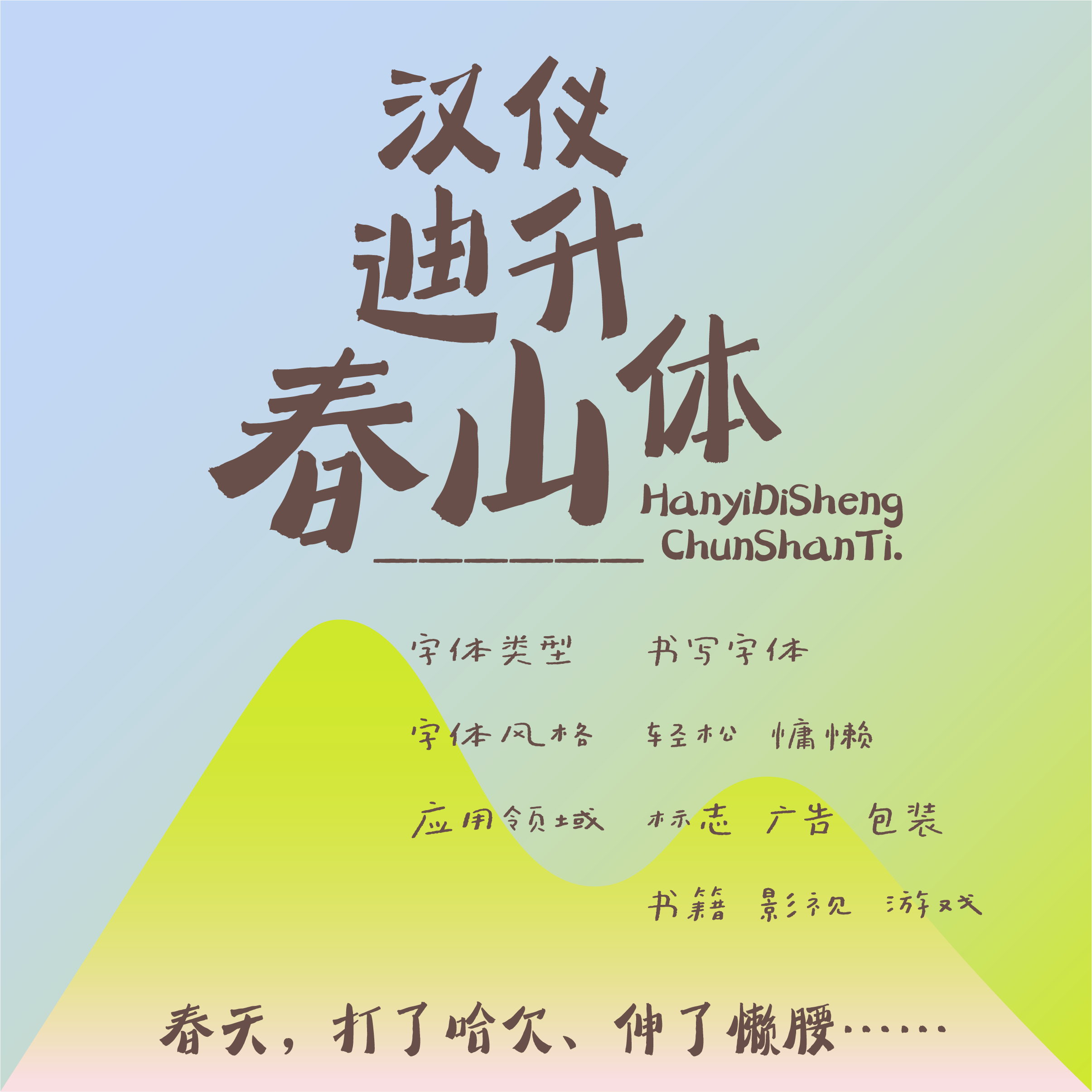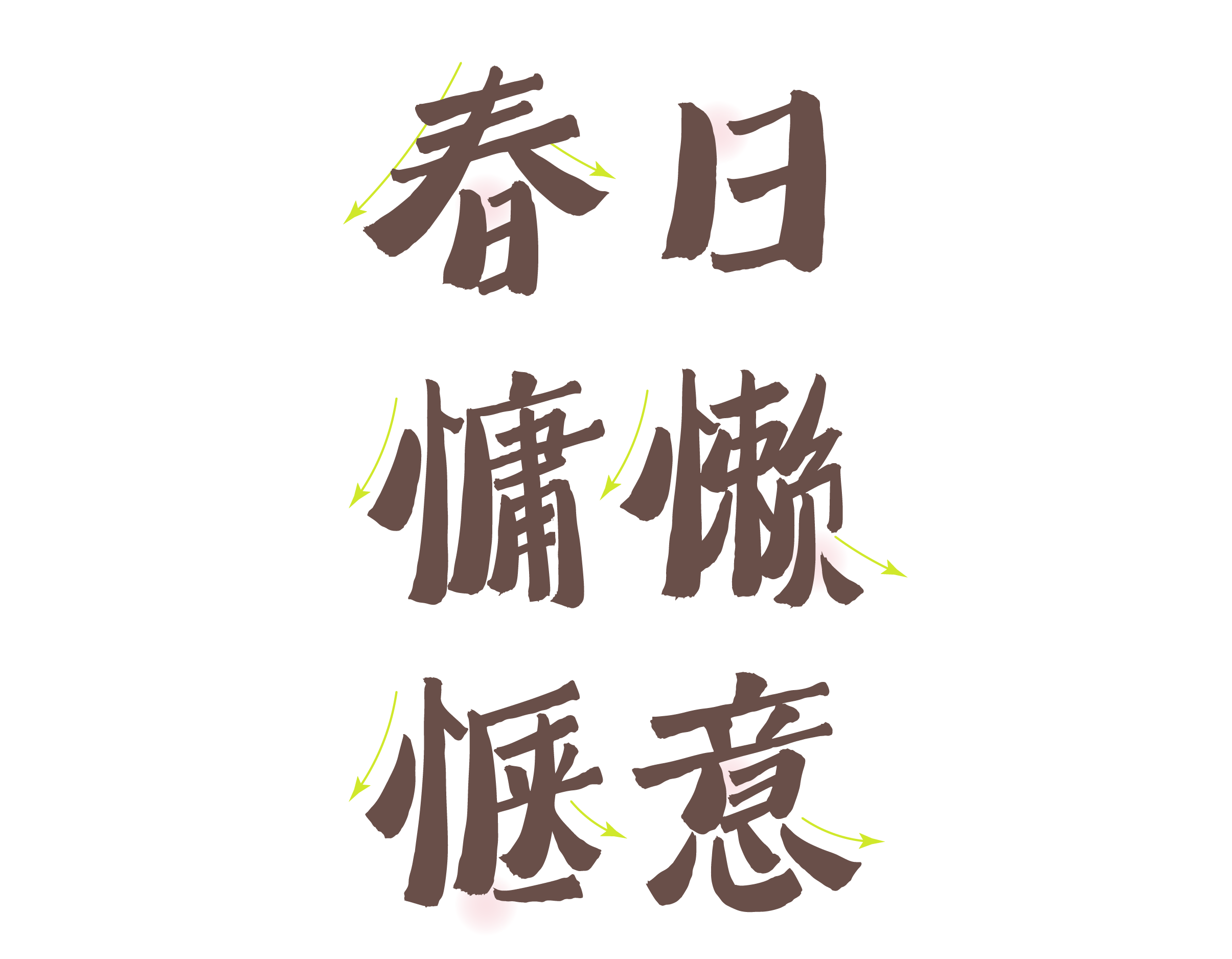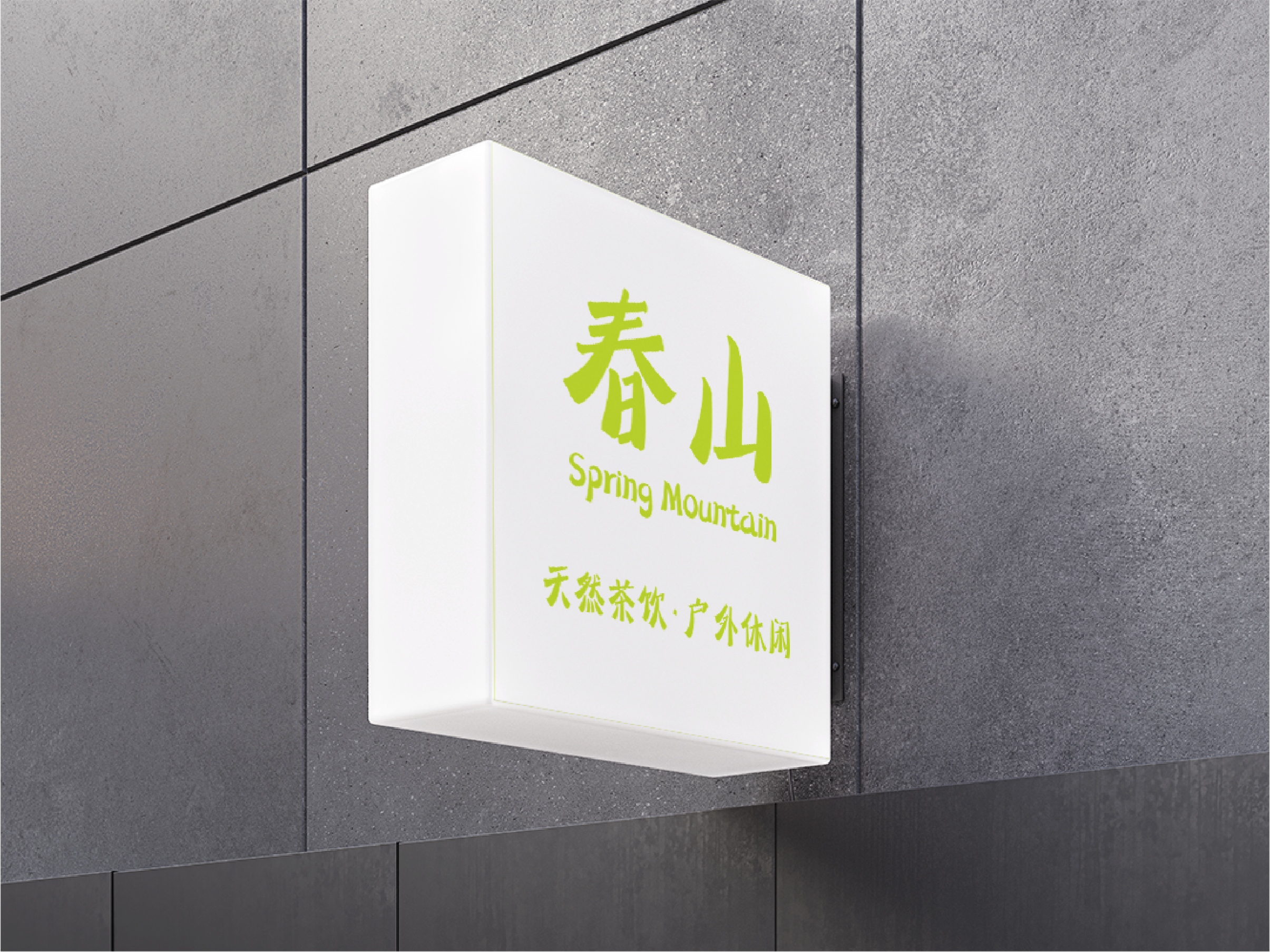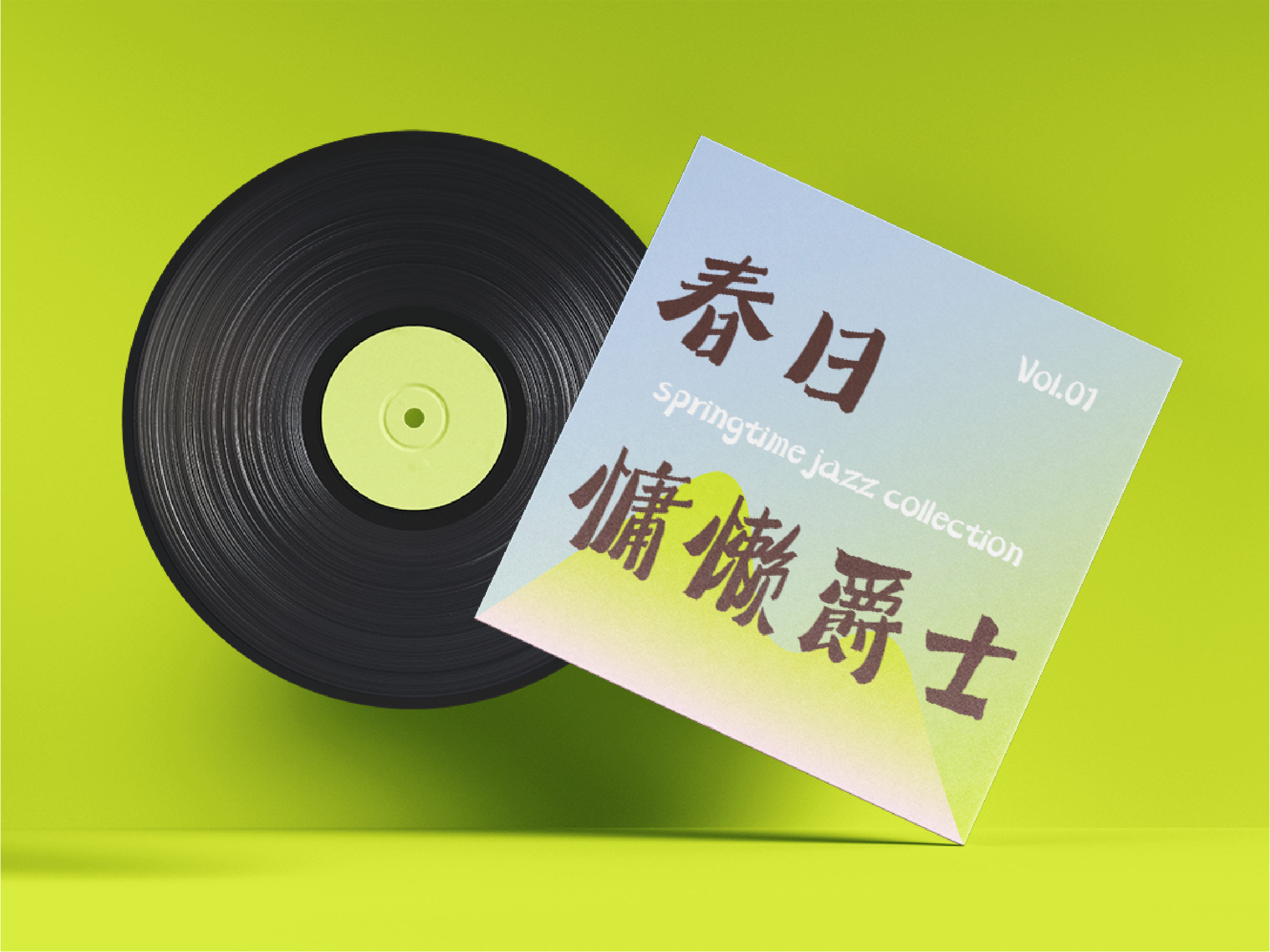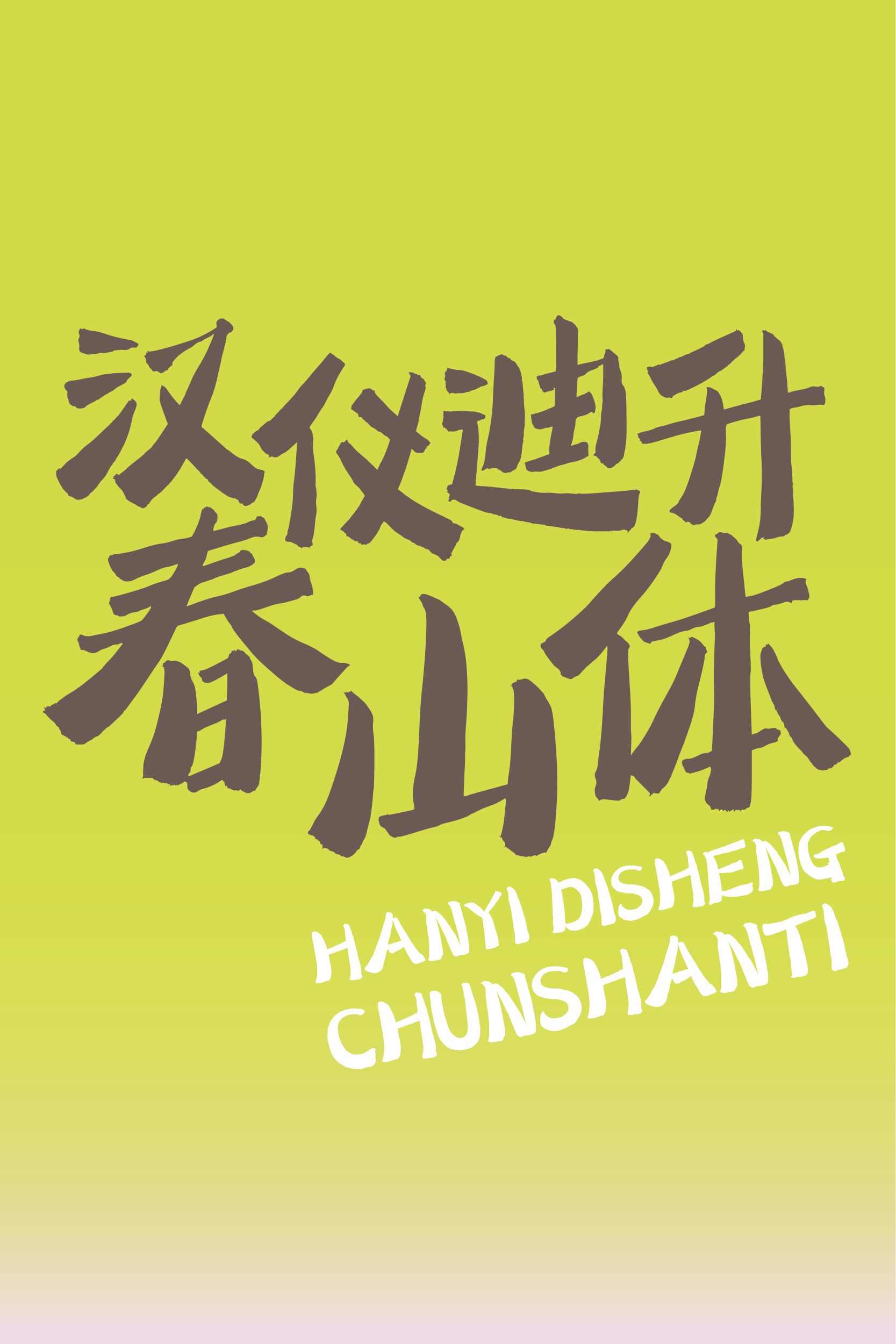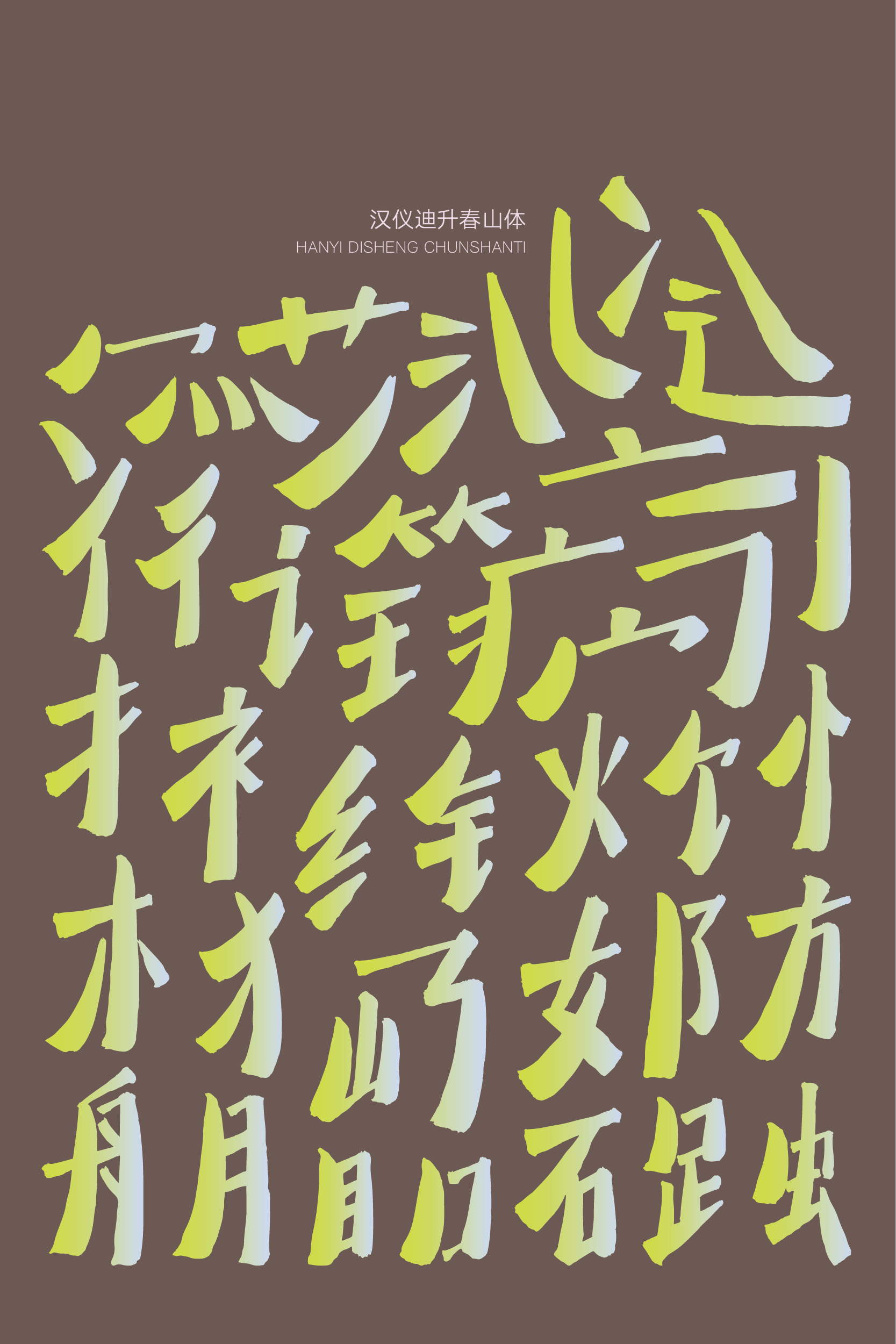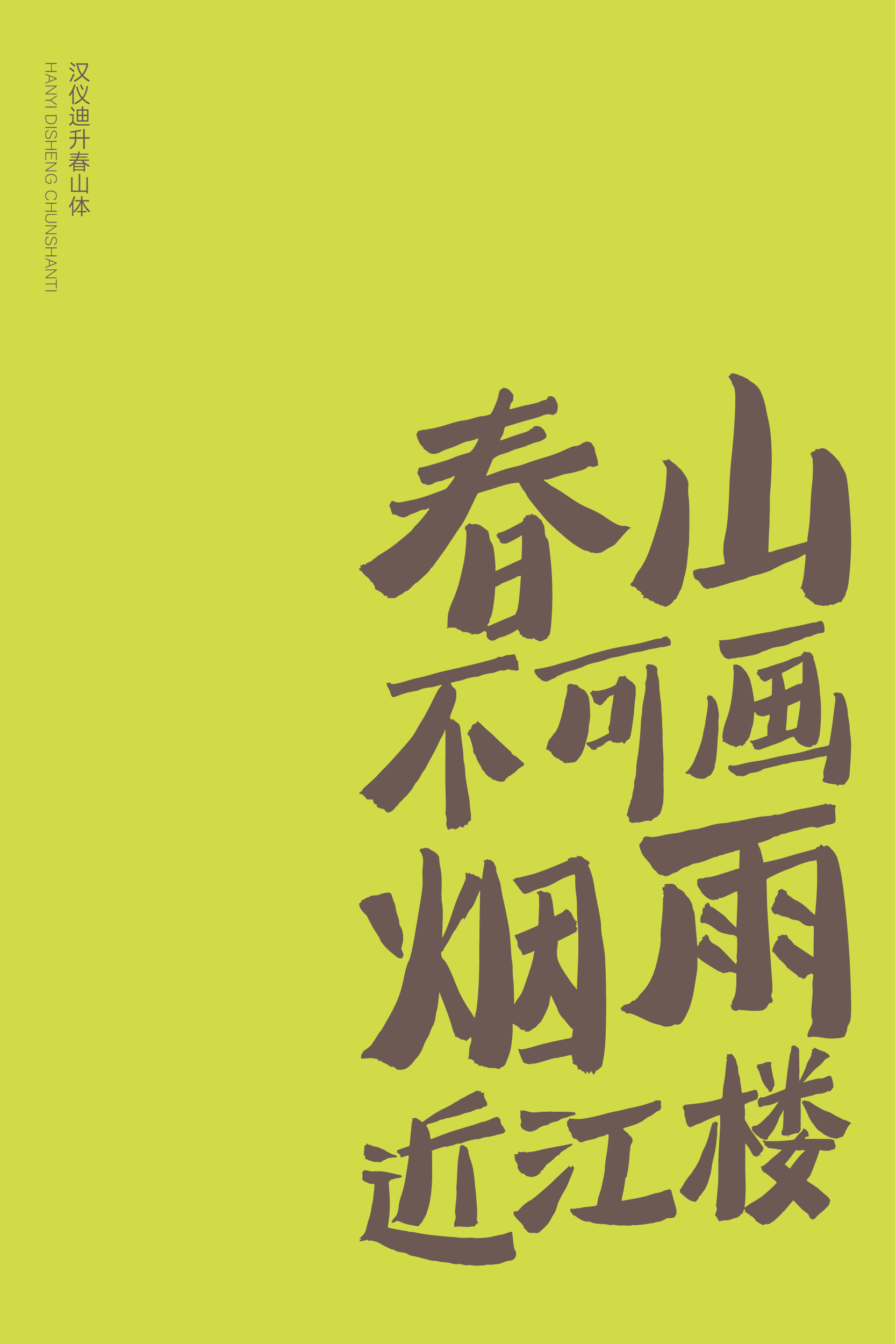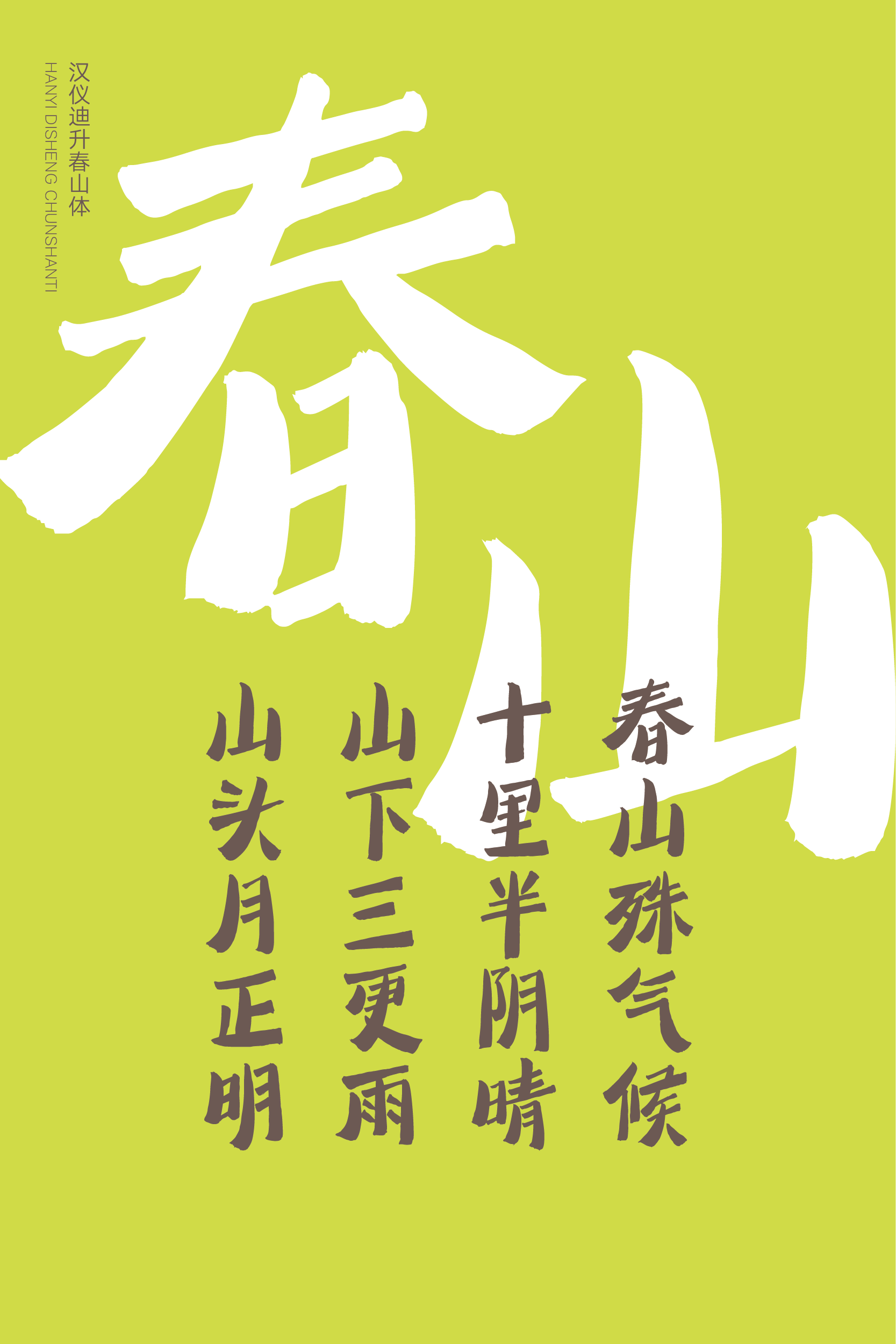
用字体书写一曲慵懒爵士
汉仪迪升春山体,像是春天从沉睡中苏醒,打了哈欠、伸了懒腰……由汉仪签约作者迪升书写的这款字体慵懒而惬意,字形姿态如同萌芽向上生长,生机勃勃,侧锋行笔,笔意放松,有呼吸感。汉仪迪升春山体适合户外休闲、图书绘本、美食餐饮等应用场景,书写一曲慵懒爵士。
字形呈向上生长的姿态,向上、向右倾斜,生机勃勃。
以放松的方笔书写,侧锋行笔。
笔画不完全搭接,有呼吸感,撇捺舒展,慵懒而松弛。
汉仪迪升春山体渲染了慵懒惬意的氛围,适合户外休闲、图书绘本、美食餐饮等轻松愉悦的应用场景。